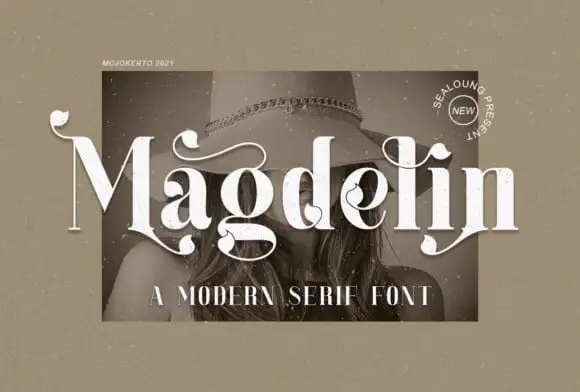
A Magdelin Serif Font é uma escolha perfeita para quem busca trazer um toque vintage a suas criações modernas. Este tipo tipográfico serif oferece formas de letras limpas e elegantes, ideal para estilos minimalistas contemporâneos. O grande diferencial desta fonte está em sua linha curva suave, uma característica que torna-a perfeita para uso nas marcas de moda ou nos editoriais. Com seu design arredondado e fluido, a Magdelin Serif atende todos os requisitos para branding fashion ou criações editoriais modernas. Experimente esta fonte em suas próximas projetos — não lhe decepcionará!